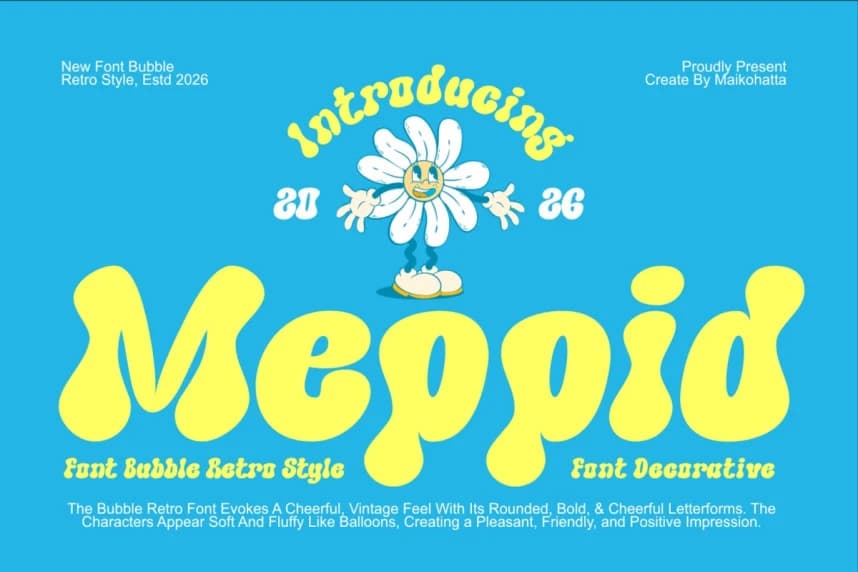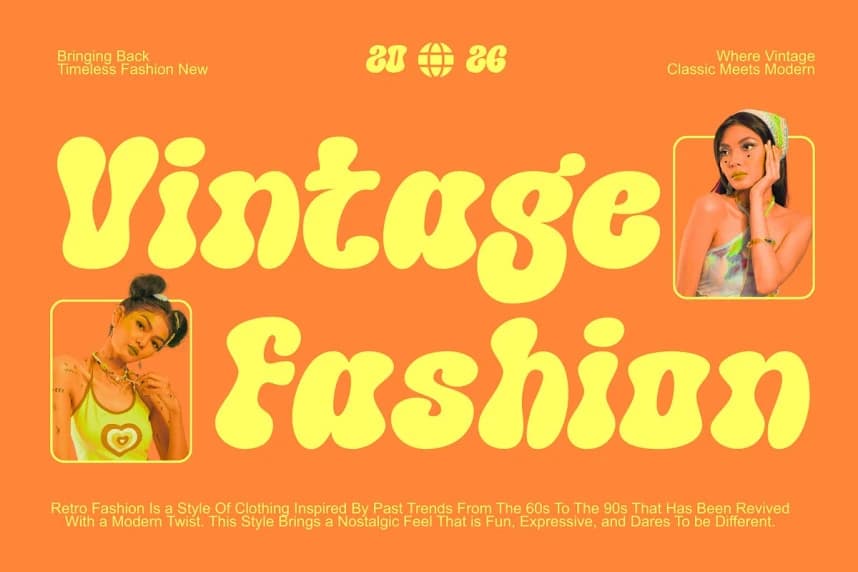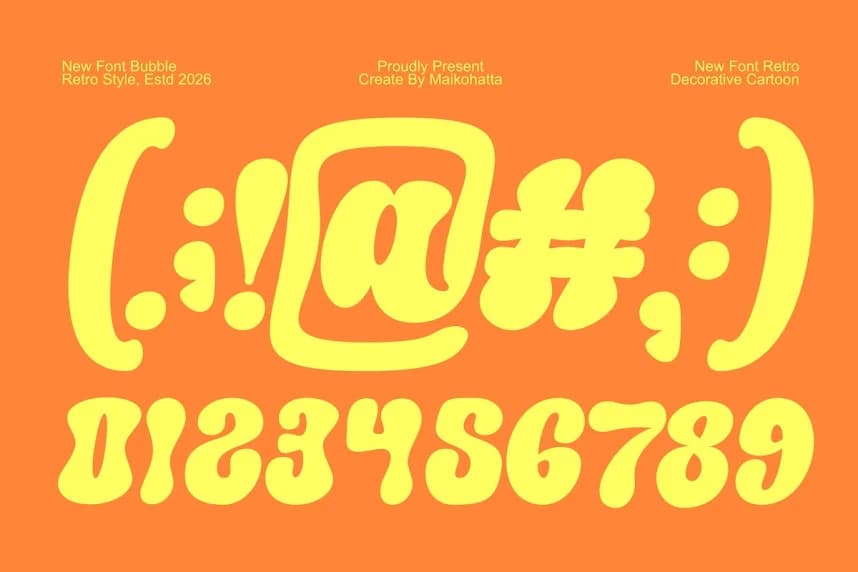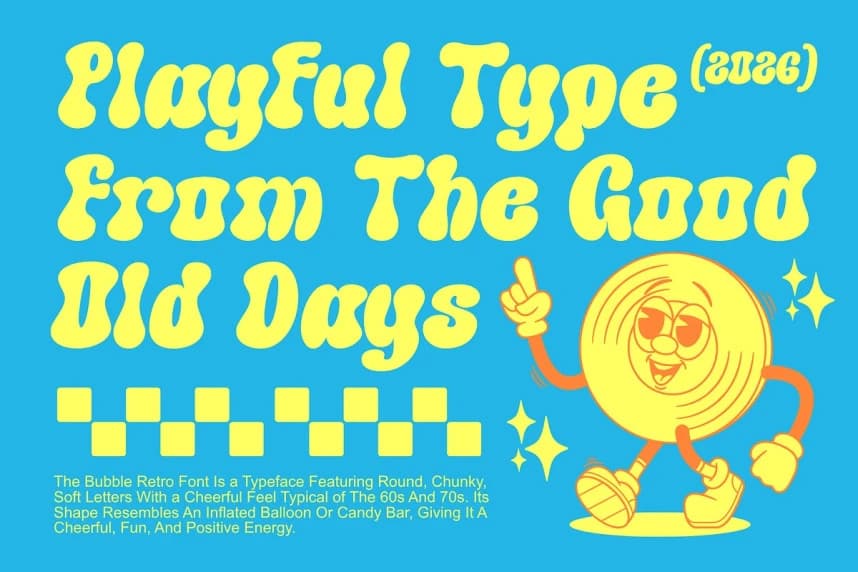
Meppid Playful Font
Meppid Playful Font, tasarımlarınıza neşeli ve oyuncu bir retro balon yazı tipi sunar ve vintage bir hava katar. Groovy 70'ler estetiğinden ilham alan bu tipografi, yumuşak, yuvarlak ve kalın harf biçimlerine sahiptir; tüylü balonlara benzeyen görünümüyle eğlenceli ve samimi bir görsel çekicilik yar
Meppid Playful Font, tasarımlarınıza neşeli ve eğlenceli bir retro balon yazı tipi sunan neşeli ve oyuncu bir yazı tipidir. 70'lerin groovy estetiğinden ilham alan bu yazı tipi, yumuşak, yuvarlak ve kalın harf biçimlerine sahip olup tüylü balonlara benzeyen bir görünüm yaratır ve bu da eğlenceli ve dostça bir görsel çekicilik sağlar.